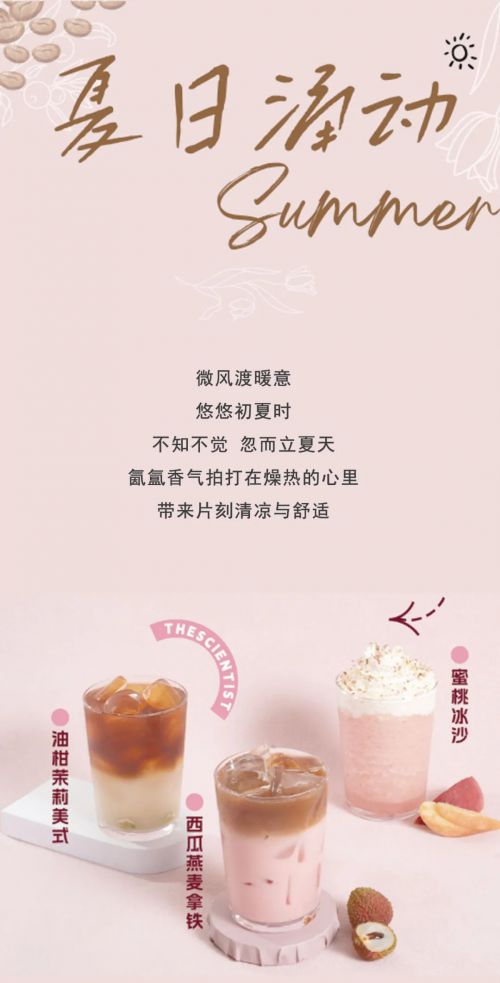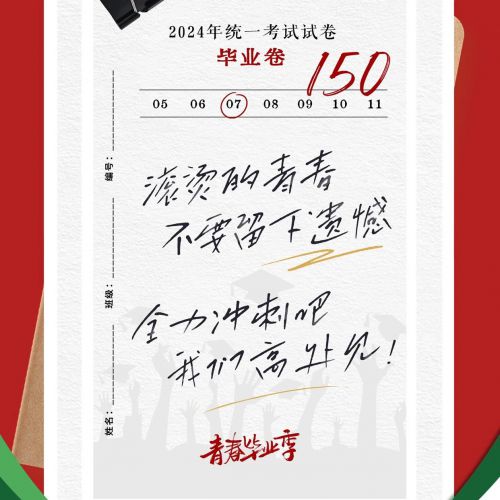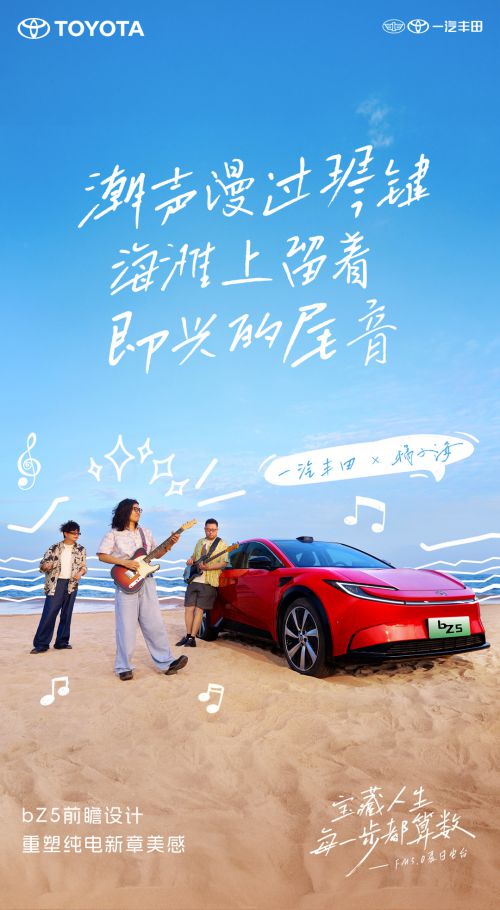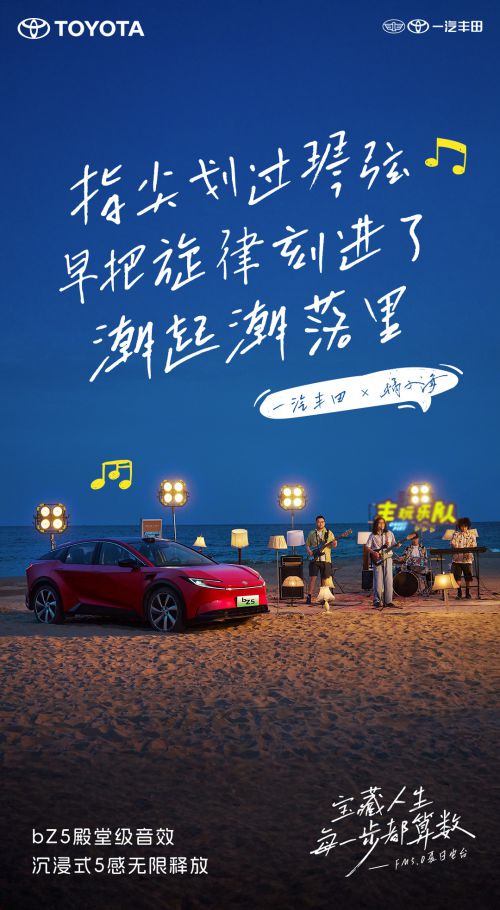
点字飒爽手写体
字库品牌: 点字库 >
点字飒爽手写体笔触长如流星穿梭,短如热泪悬眶,结构展如烟花绽放,束如心事深藏。点字飒爽手写体抛弃了复杂琐碎的钩画细节,使字体简洁明快,利落大方,力求摆脱传统书写的结构束缚,漫意纸上,在乱与整,动与静,开与合之间寻求微妙的平衡。细细观赏,又如你我的青春年华,看似漫不经心,却又余味悠长。